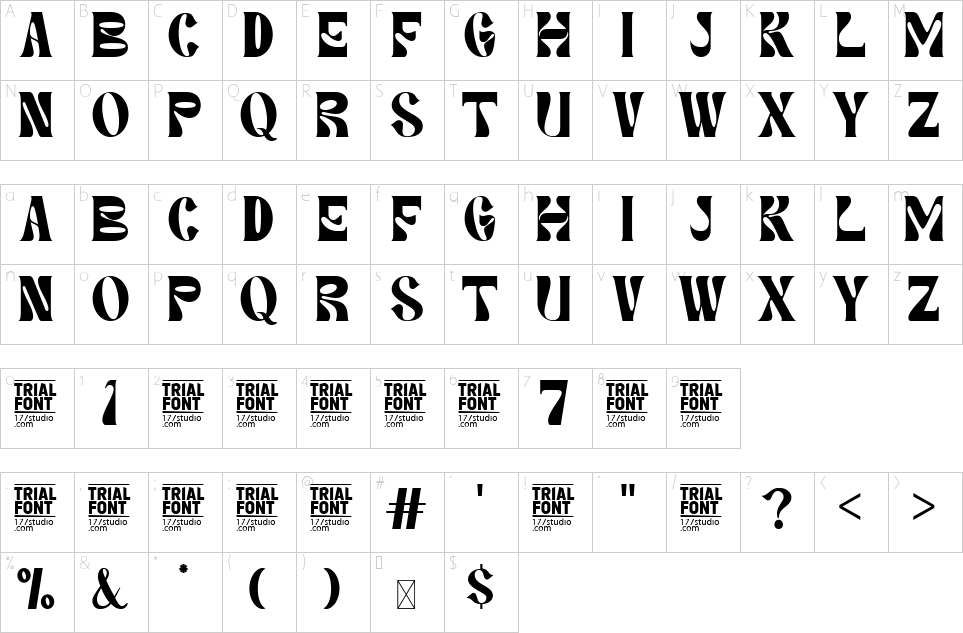
Generate Changes Font
A fonte ‘Generate Changes’ é uma escolha perfeita para designers que procuram novas opções para suas criações digitais. Desenvolvida pela 177studio.com, esta font foi projetada com um design moderno e versátil que combina facilmente em qualquer layout visual. O download da font ‘Generate Changes’ é fácil de fazer e disponível tanto para sistemas Windows quanto Mac, fazendo-a uma opção conveniente para designers do Brasil e mundo afora. Essencial para quem busca adicionar um toque único à sua obra, este design gráfico abrange vários estilos, desde linhas clean até texturas mais elaboradas. A fonte ‘Generate Changes’ pode ser usada em variados tipos de projetos, como criações digitais, materiais de marketing digital ou simplesmente para dar vida a designs gráficos pessoais. Com apenas um clique no seu sistema, você terá acesso a uma fonte que não só se destaca pela sua qualidade estética mas também por ser gratuita, tornando-a ainda mais acessível e inclusiva para designers em todos os níveis.
Mapa de caracteres da fonte Generate Changes Font